시각보정, 글자의 완성도를 결정짓다
시각보정이 뭔가요?
시각보정(Optical Adjustment)은 글자 디자인 시 발생하는 착시 현상들을 방지하고 글자의 시각적 결함을 찾아내어 글자의 디자인을 세밀하게 조정하는 작업을 말합니다. 시각보정은 글자의 가독성과 판독성에 지대한 영향을 끼치기 때문에, 폰트디자인에 있어 가장 핵심이라고 할 수 있습니다.
1. 획의 두께 대비 (Stroke Width Contrast)
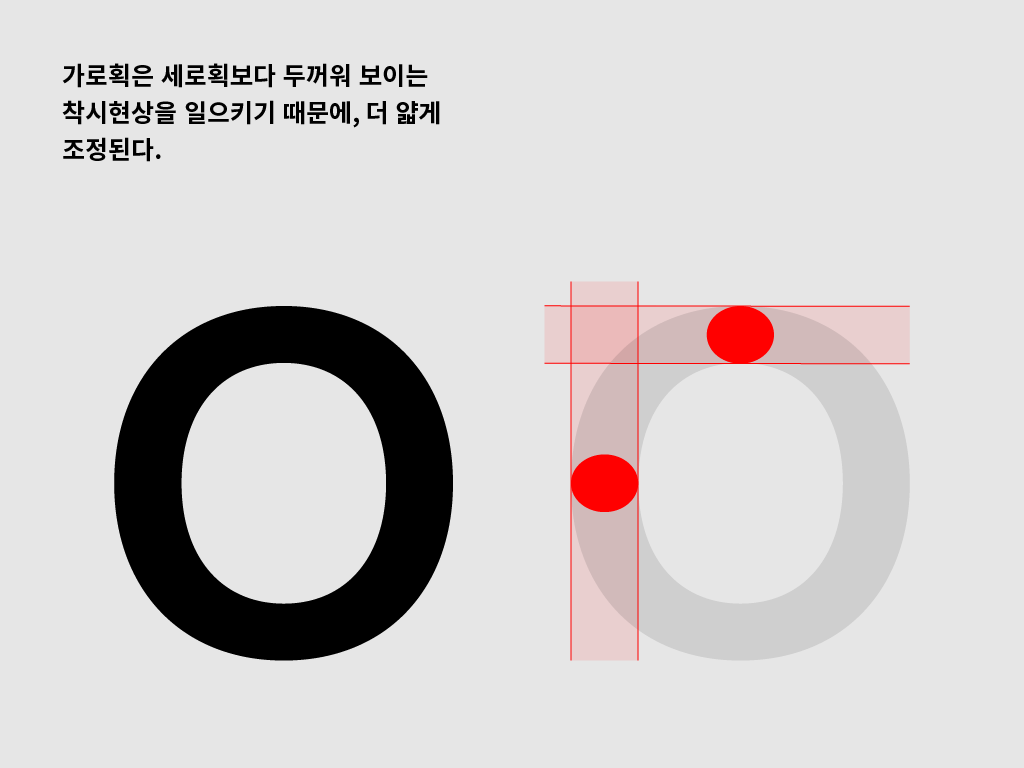
일반적으로 우리 눈은 세로획보다 가로획을 두껍게 인식합니다. 그렇기 때문에 가로획을 더 얇게 조정해야 글자 전체의 획이 균일하게 보이도록 만들 수 있습니다. 이 대비는 글자의 형태에 따라 달라지기 때문에, 계속 테스트해보며 최적의 대비를 찾아야 합니다.
이 대비는 글자가 두꺼워질수록 커지고, 얇아질수록 작아지기 때문에 여러 두께의 폰트를 제작할 경우, 각각의 폰트에 알맞은 대비를 적용하세요.
2. 사선의 획 두께 (Diagonal Stroke Width)
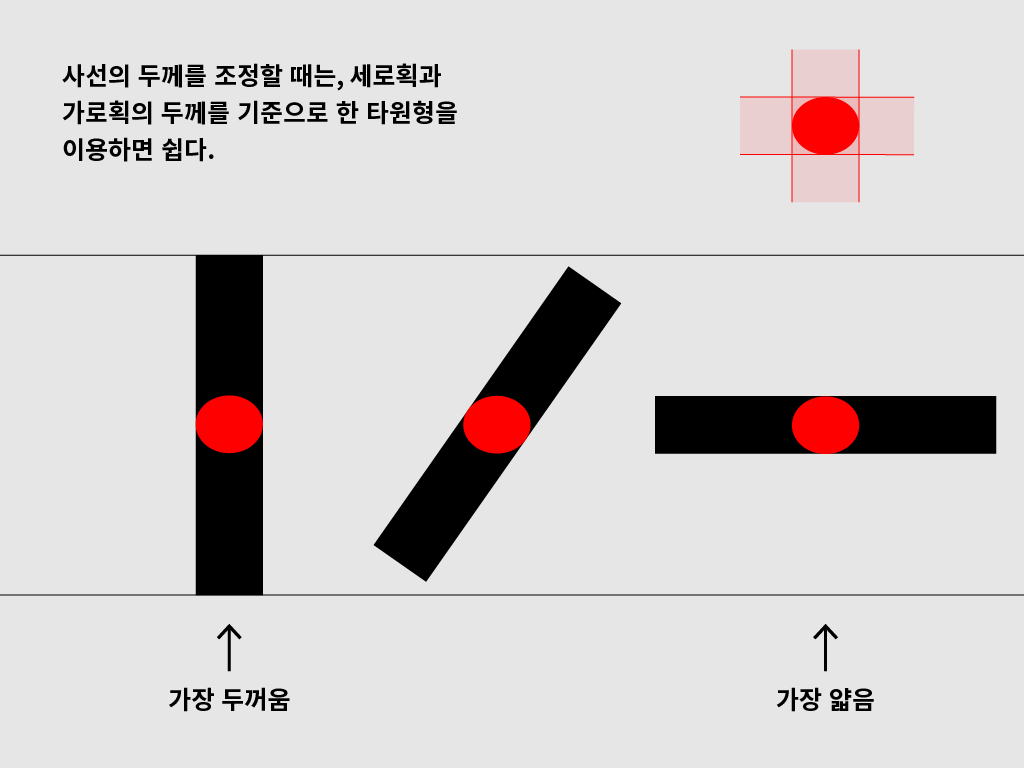
사선획의 두께를 정해야 할 때는 세로획과 가로획의 두께를 기준으로 한 타원형을 이용하면 손쉽게 조정할 수 있습니다. 획의 두께가 타원형의 외곽을 접하도록 하세요.
3. 오버슛 (Overshoot)
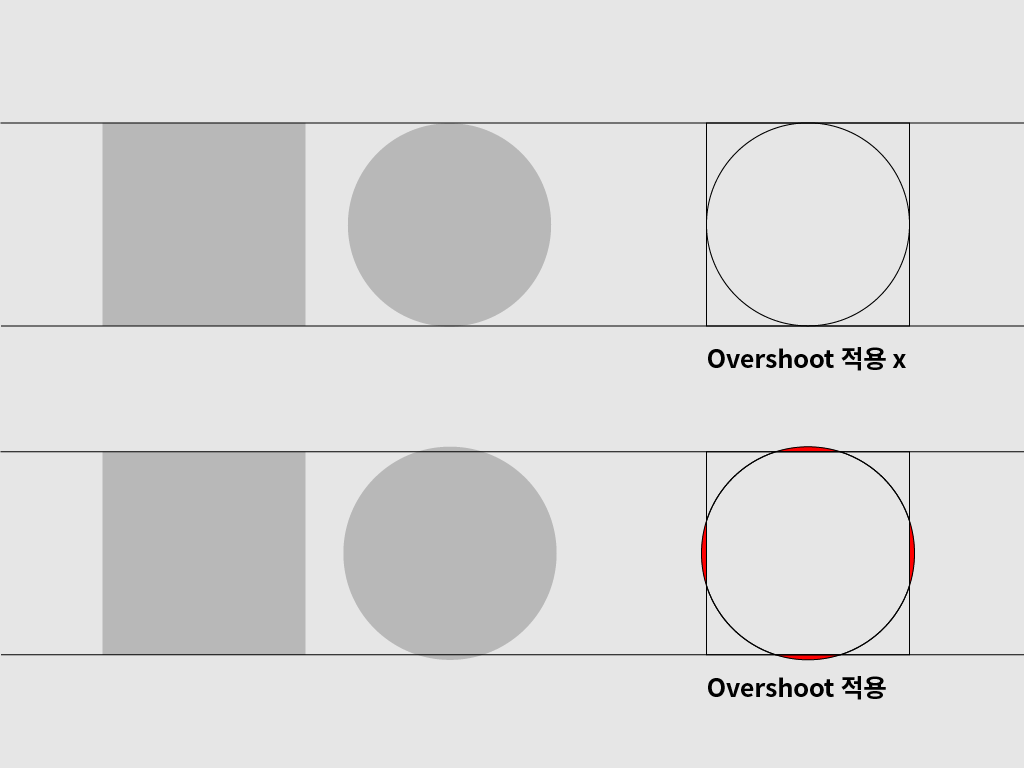
위의 예시를 보면 사각형의 부피가 원보다 크기 때문에 같은 높이지만 사각형이 원보다 커보입니다. 따라서 원의 크기를 사각형보다 크게 조정했습니다. 도형이 기준선 밖으로 넘어간 부분을 Overshoot이라고 칭합니다. H와 O와 같이 서로 다른 모양의 글자들을 디자인할 때, 이와 같은 Overshoot이 필수적으로 적용됩니다.
4. 글자의 관절 (Joint)
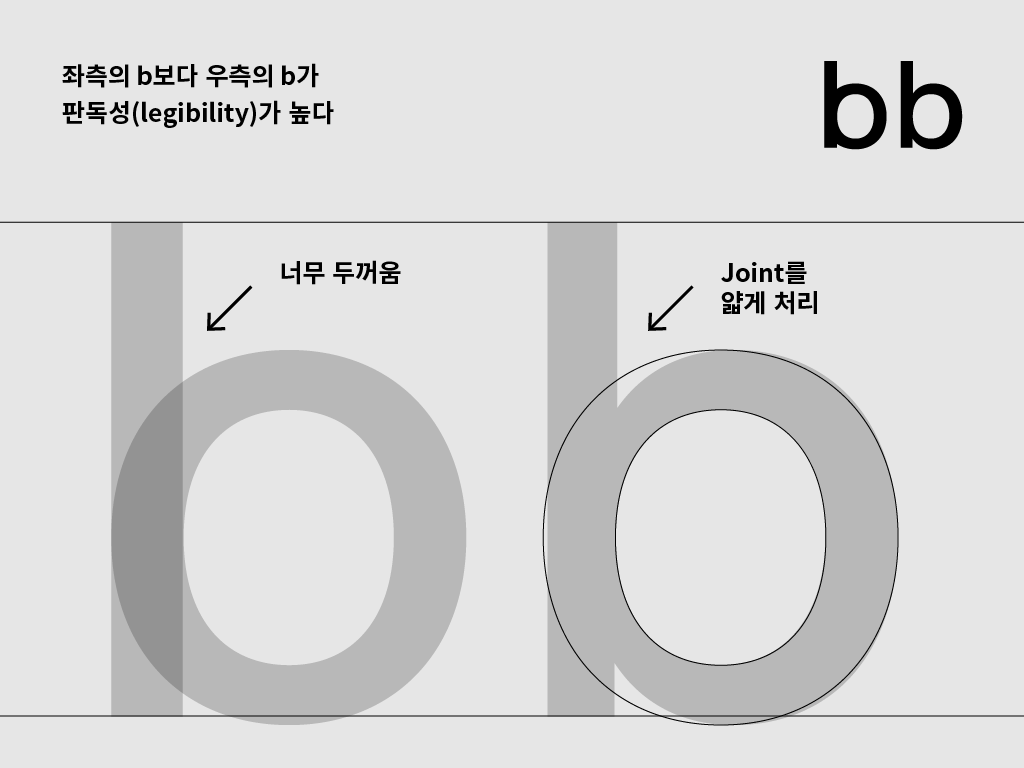
서로 다른 획들이 합쳐지는 부분을 Joint라고 합니다. 글자 b를 예시로 들자면 Joint가 너무 두꺼워 글자가 선명하지 않고 둔해보입니다. 이 joint 부분을 깎아내면 소형 화면에서 글자가 뭉쳐 보이는 현상을 방지할 수 있고, 글자의 판독성(legibility) 또한 개선할 수 있습니다.
5. 시각적 중심 (Optical Center)
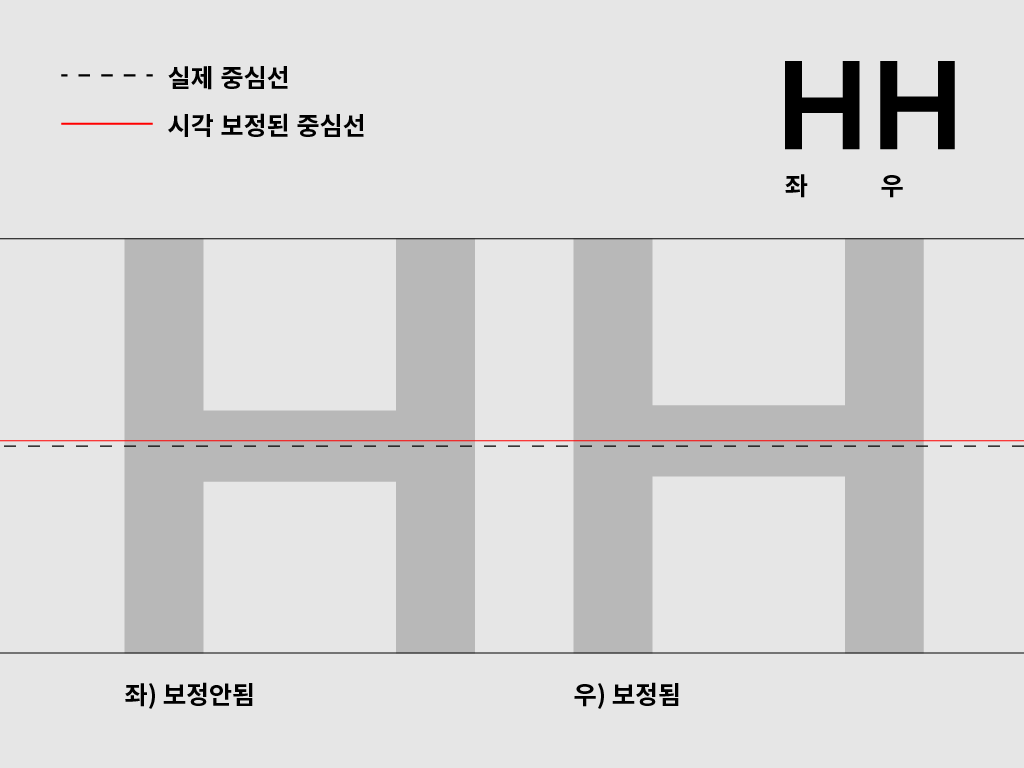
우리의 눈은 글자의 중심선이 실제 중심선보다 낮다고 착각합니다. 이러한 착시 현상을 방지하기 위하여 알파벳 H나 E와 같이 Crossbar가 있는 글자들은 실제 중심선보다 높게 조정해야 합니다.
6. 여백과 크로스바 (Negative Space and Crossbar)
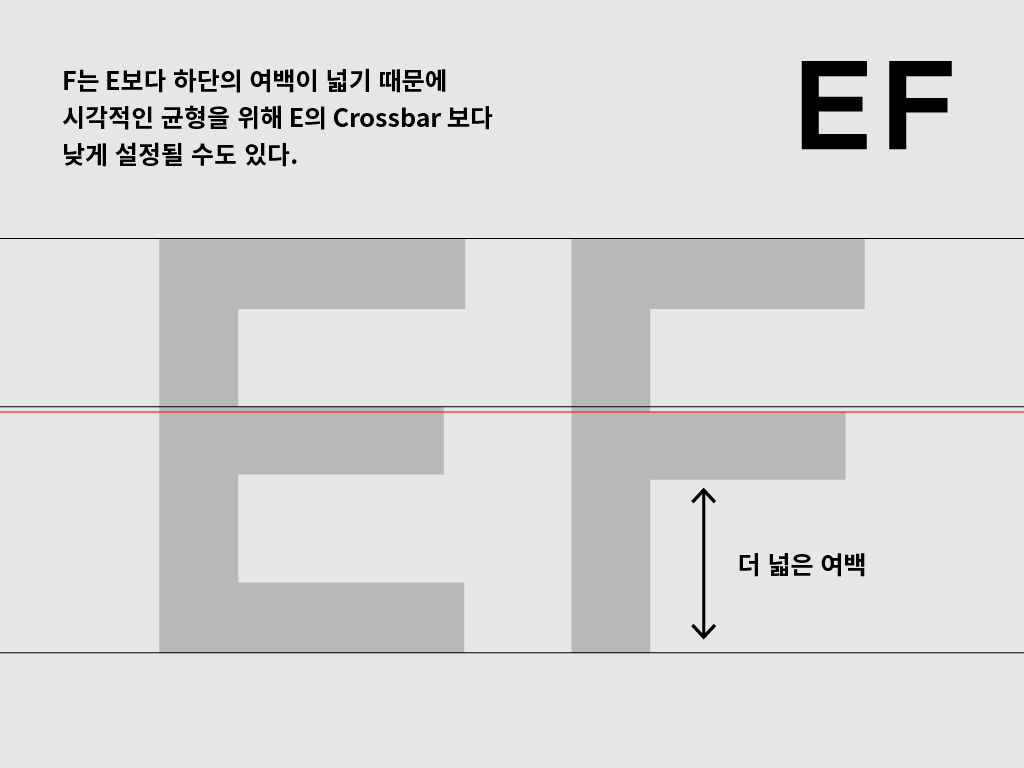
E와 F는 거의 같은 모양이지만 F의 하단 여백이 더 넓기 때문에 F의 크로스바를 E보다 살짝 낮게 조정하는 경우도 있습니다, E와 F와 같은 방식으로 P와 R 또한 디자인합니다.
7. 교차하는 획 (Crossing Strokes)
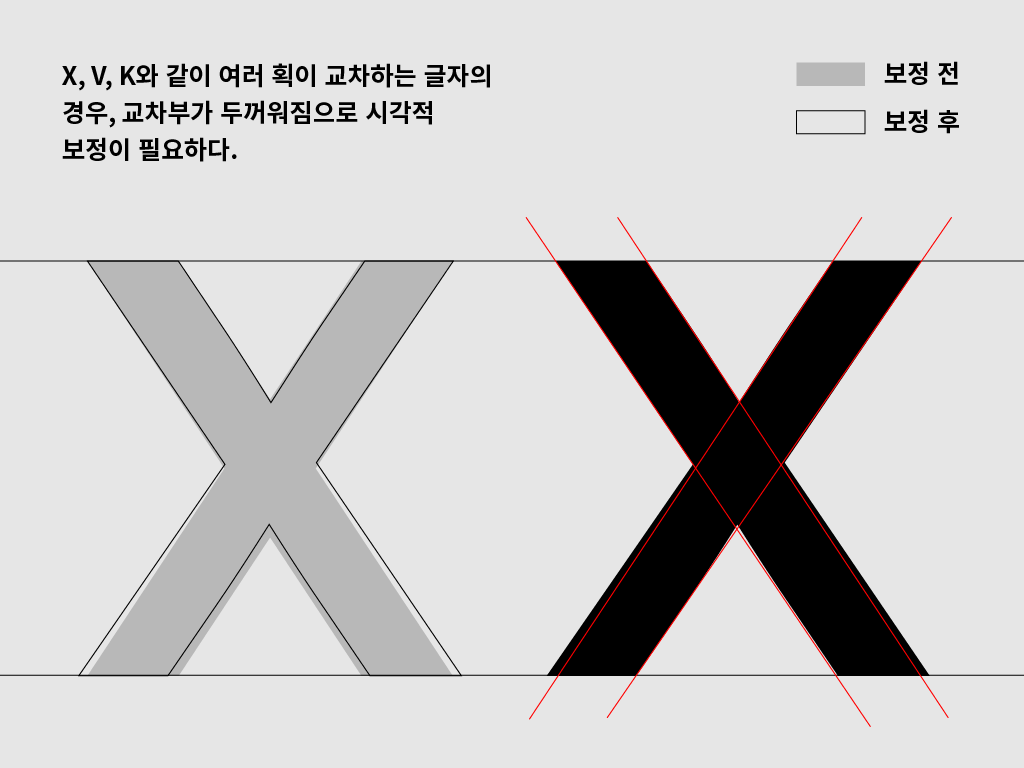
산세리프체들의 X를 보면 교차하는 획들이 실제로는 일직선이 아니고 중심으로 갈수록 얇아지는 것을 확인할 수 있는데, 이는 획이 교차 지점이 두꺼워지는것을 방지하기 위해서입니다. X와 마찬가지로 여러 직선이 교차하는 K, V, W, Y 글자들 모두 시각보정이 필요합니다.
8. S자 (The "S")
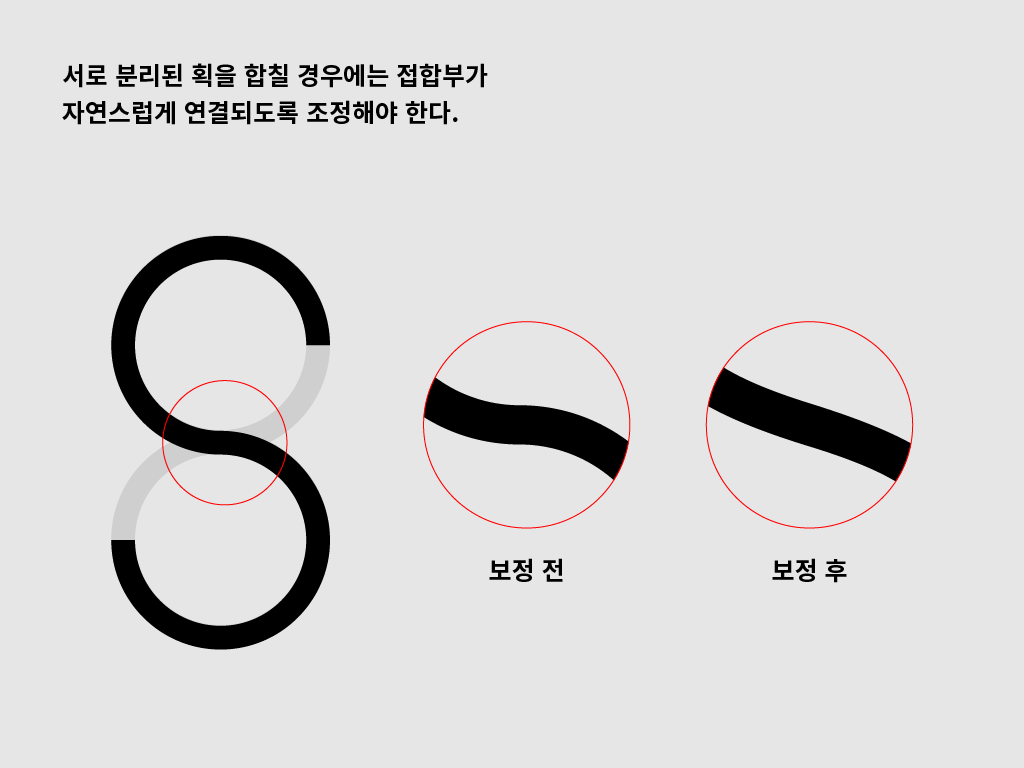
S는 알파벳 중 디자인하기 제일 까다로운 글자입니다. 일반적으로 두 개의 반원을 잘라 합치는 형태로 많이 디자인하는데, 접합부분을 그대로 붙이게 되면 매우 어색한 형태가 될 수 있습니다. 따라서 베지어 핸들(곡선의 완곡을 조절하는 툴)을 세밀하게 조정하여 하나의 이어진 획처럼 수정하는 것이 핵심입니다.
9. 속공간과 너비 (Counter and Width)
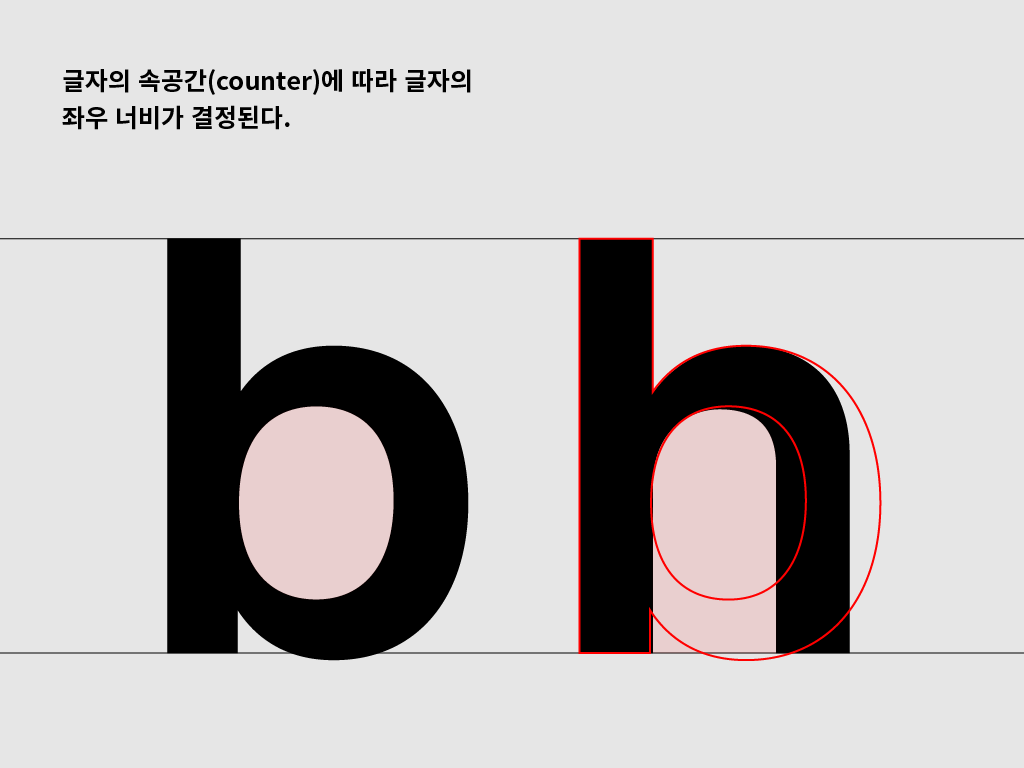
b와 h처럼 같은 디자인을 공유하는 글자의 경우라 할지라도 글자의 속공간에 따라 글자의 너비가 알맞게 조정되어야 합니다. 위의 예시를 보면 b의 갇힌 공간(counter)보다 h의 공간이 크기 때문에 h의 좌우 너비가 bb보다 좁게 조정된 것을 볼 수 있습니다.